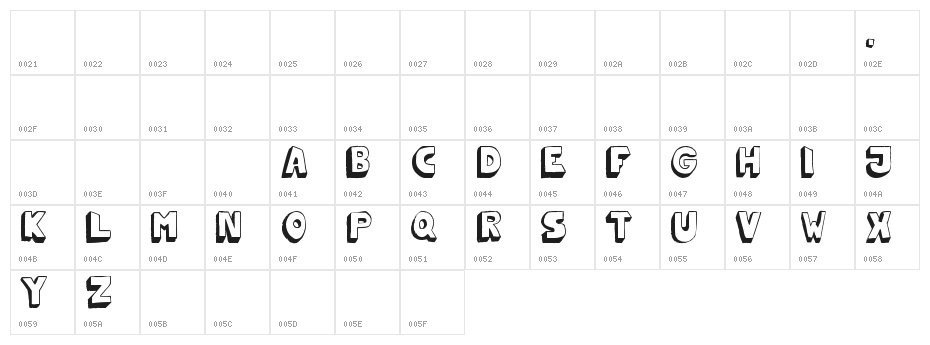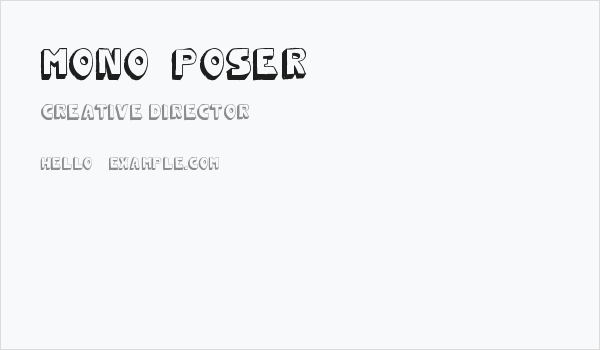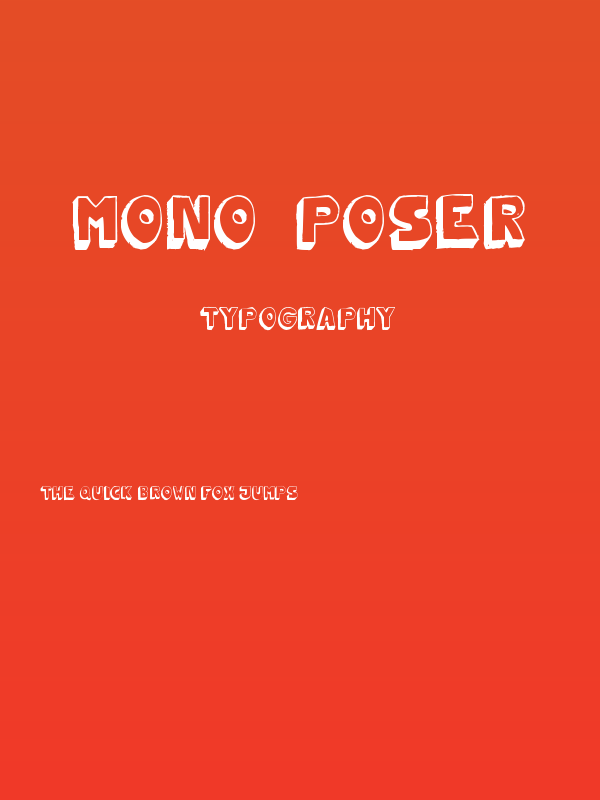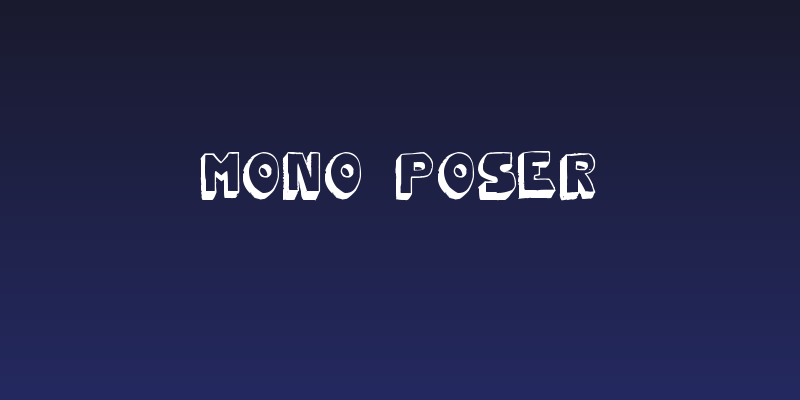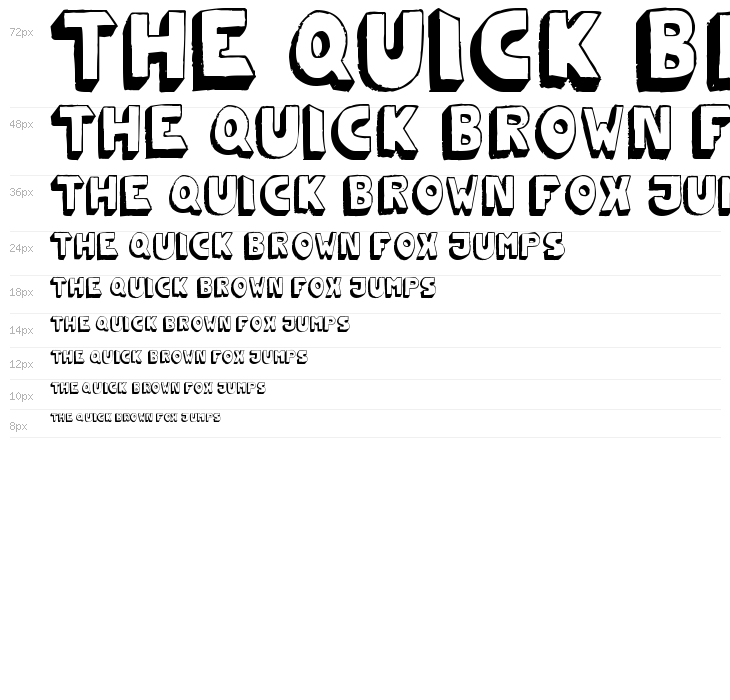
Mono2poser Font
| Gesamtstil | Playful, Dynamic |
| Vorgeschlagene Projekte | Perfect for comic book titles, children's book covers, playful branding, and posters. |